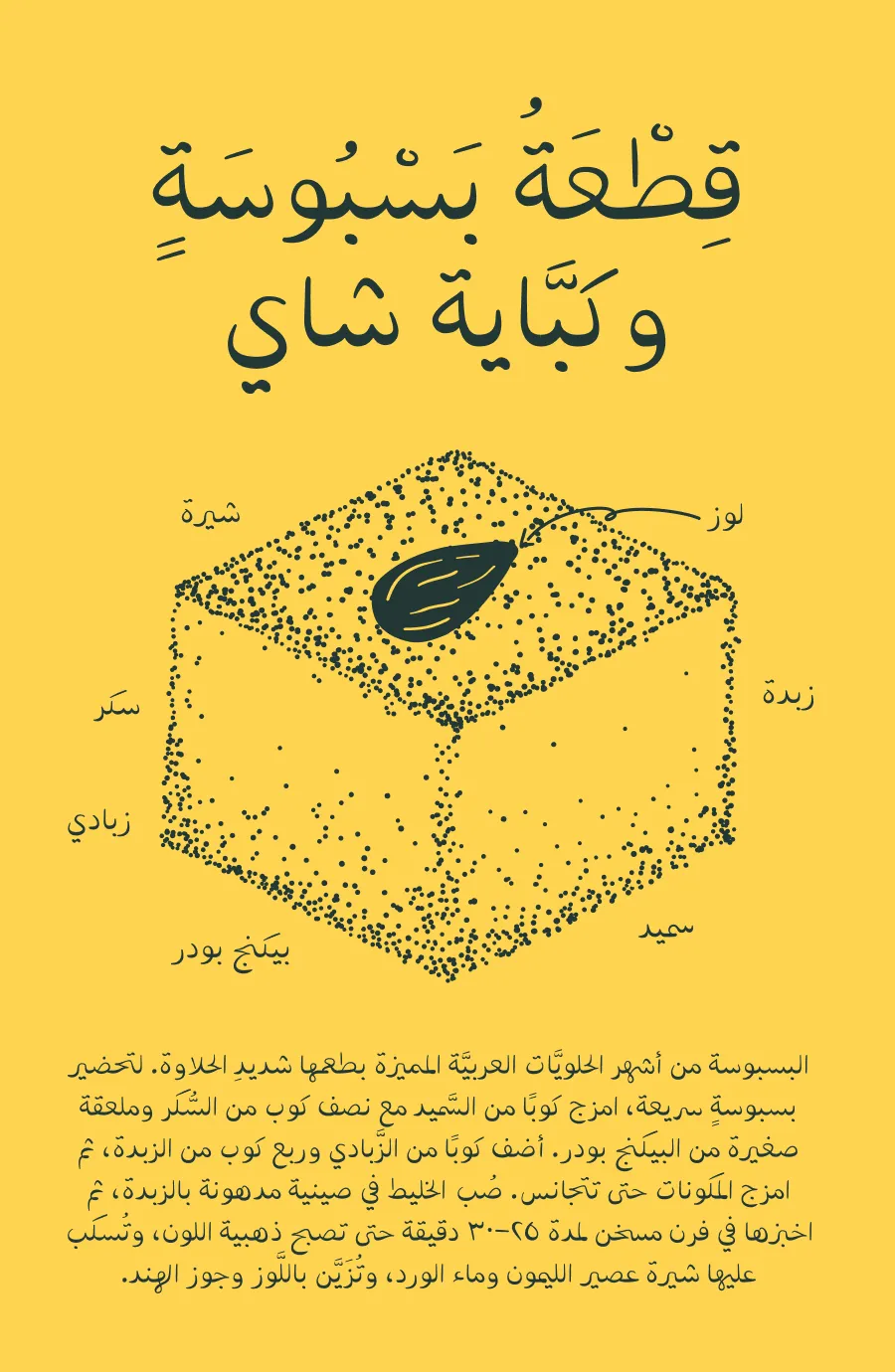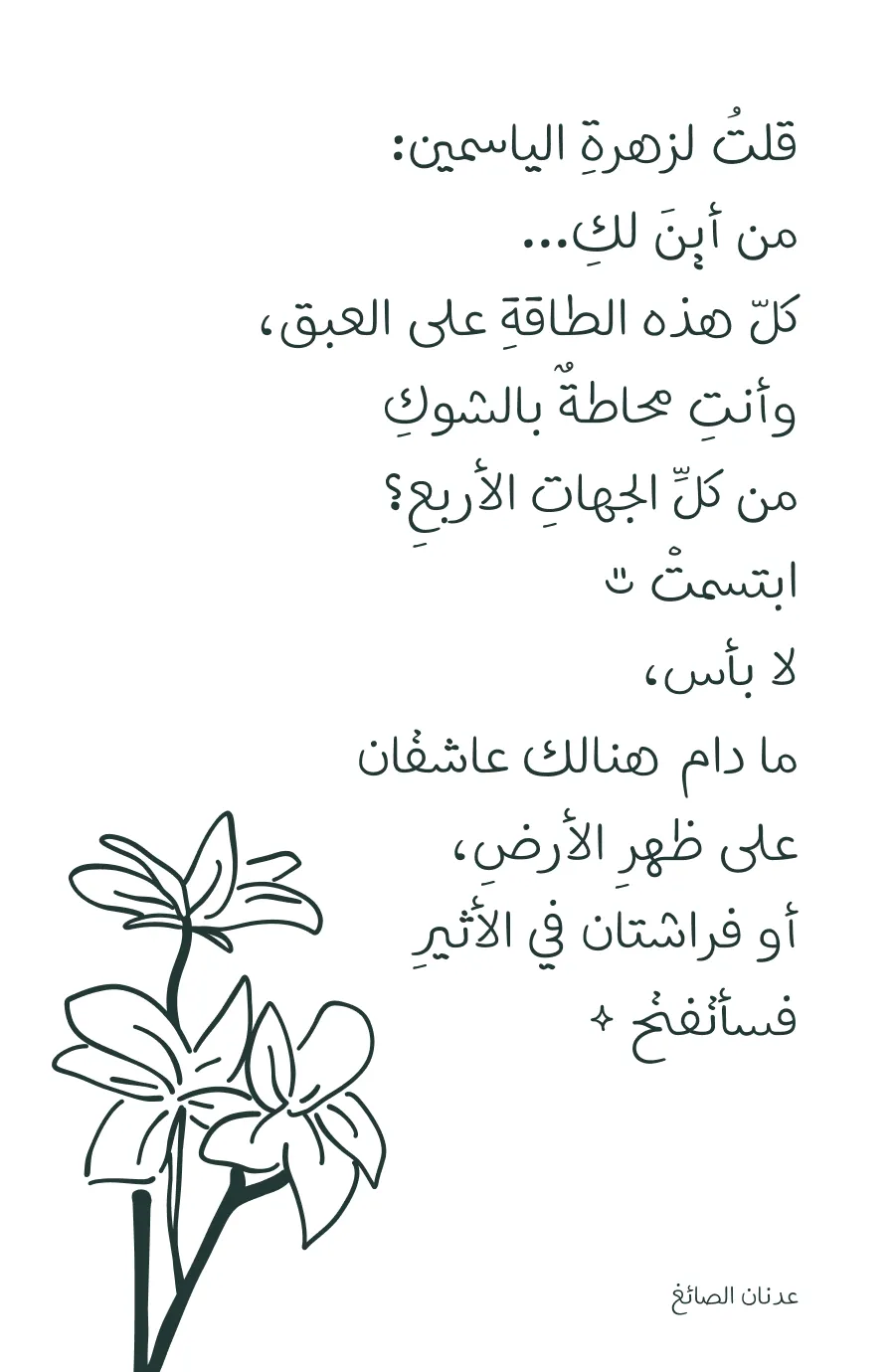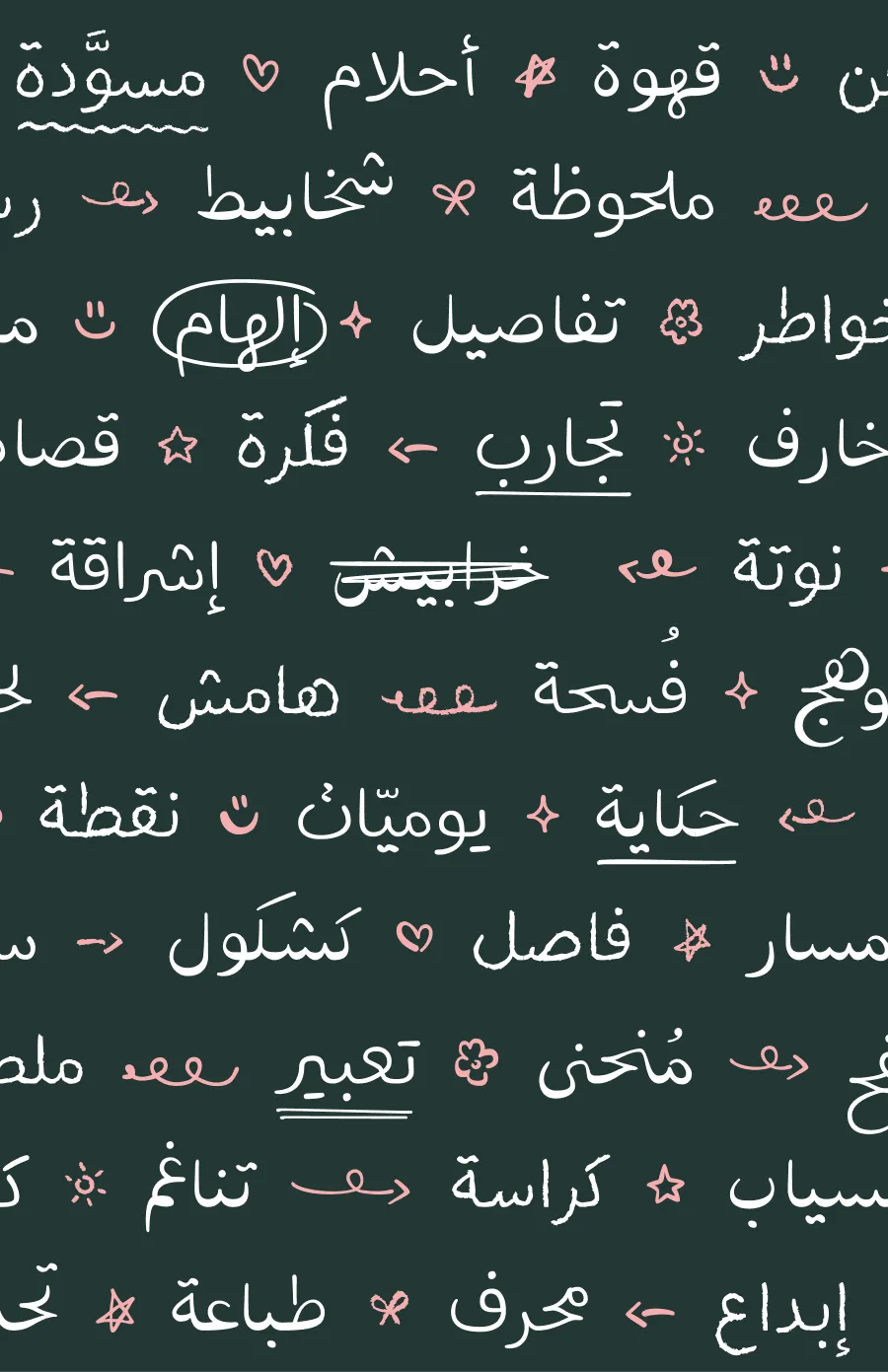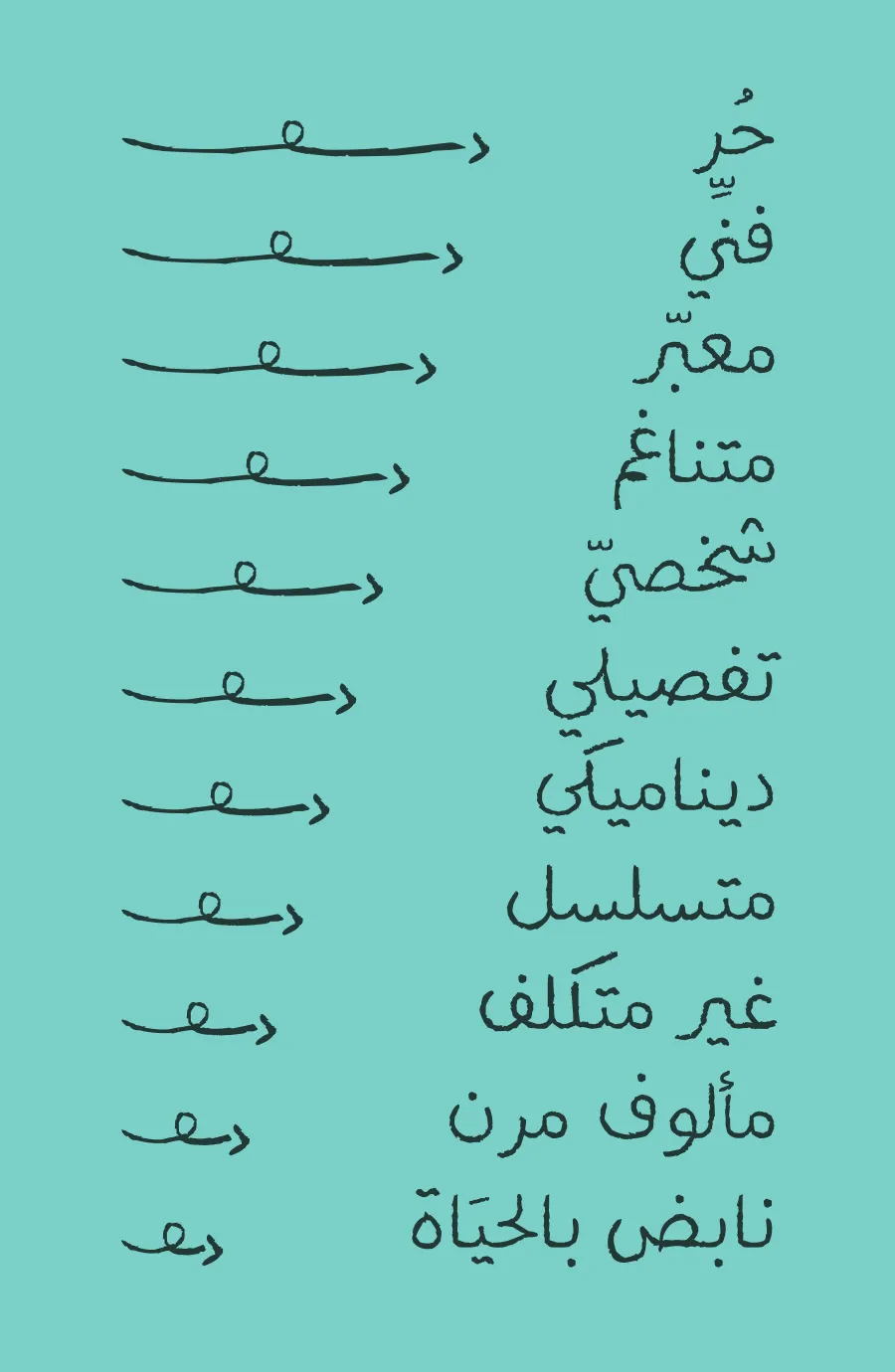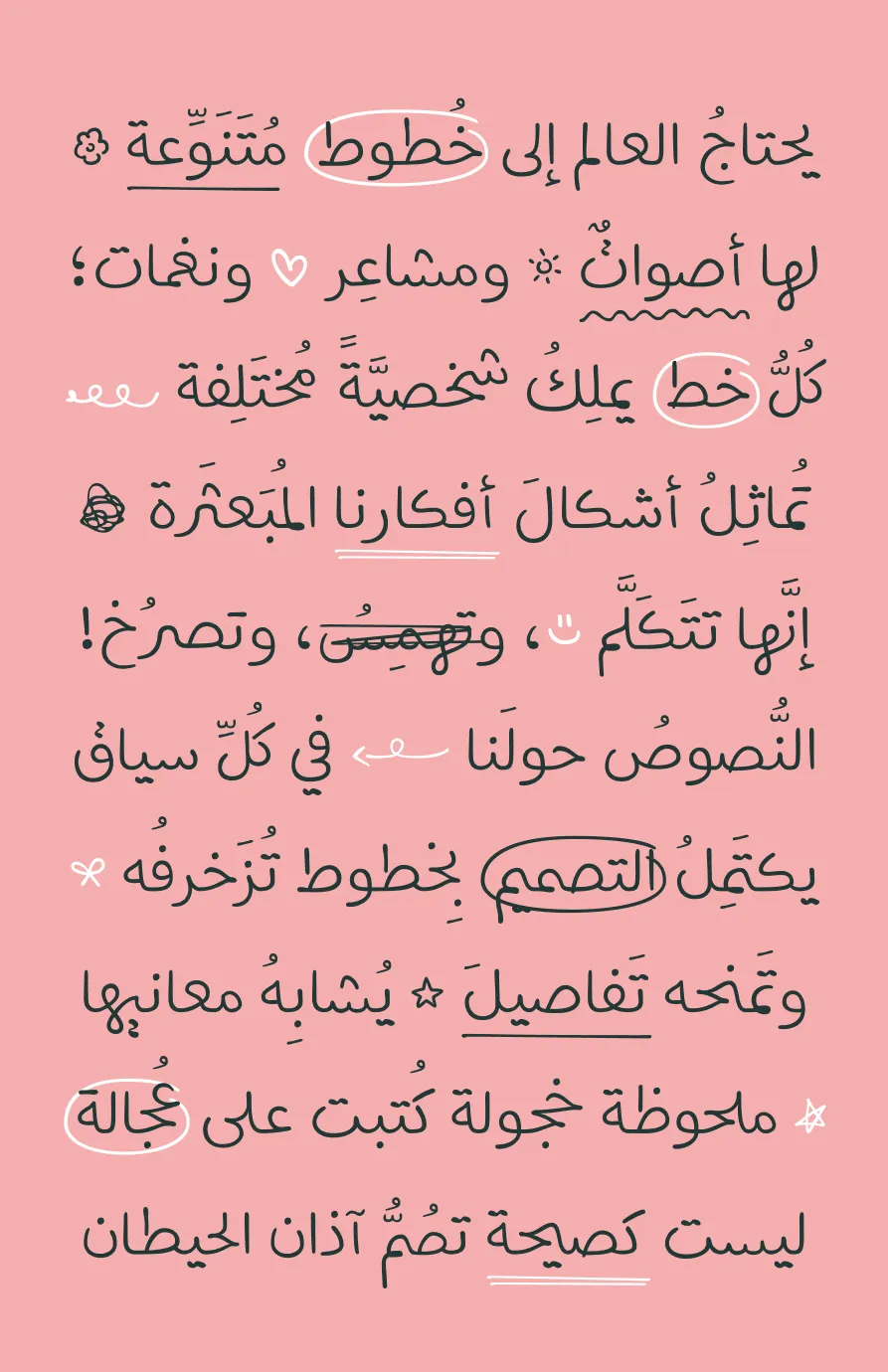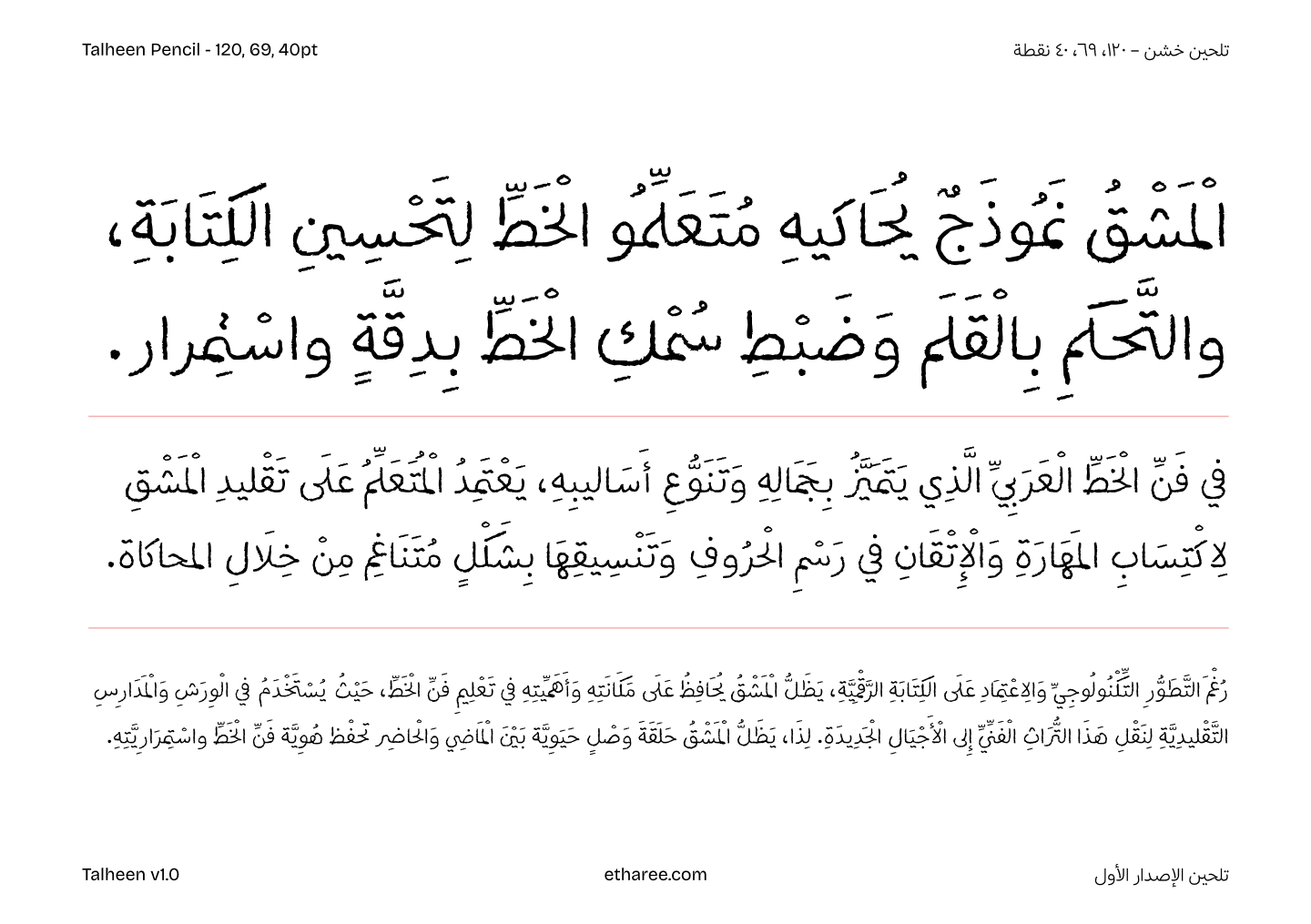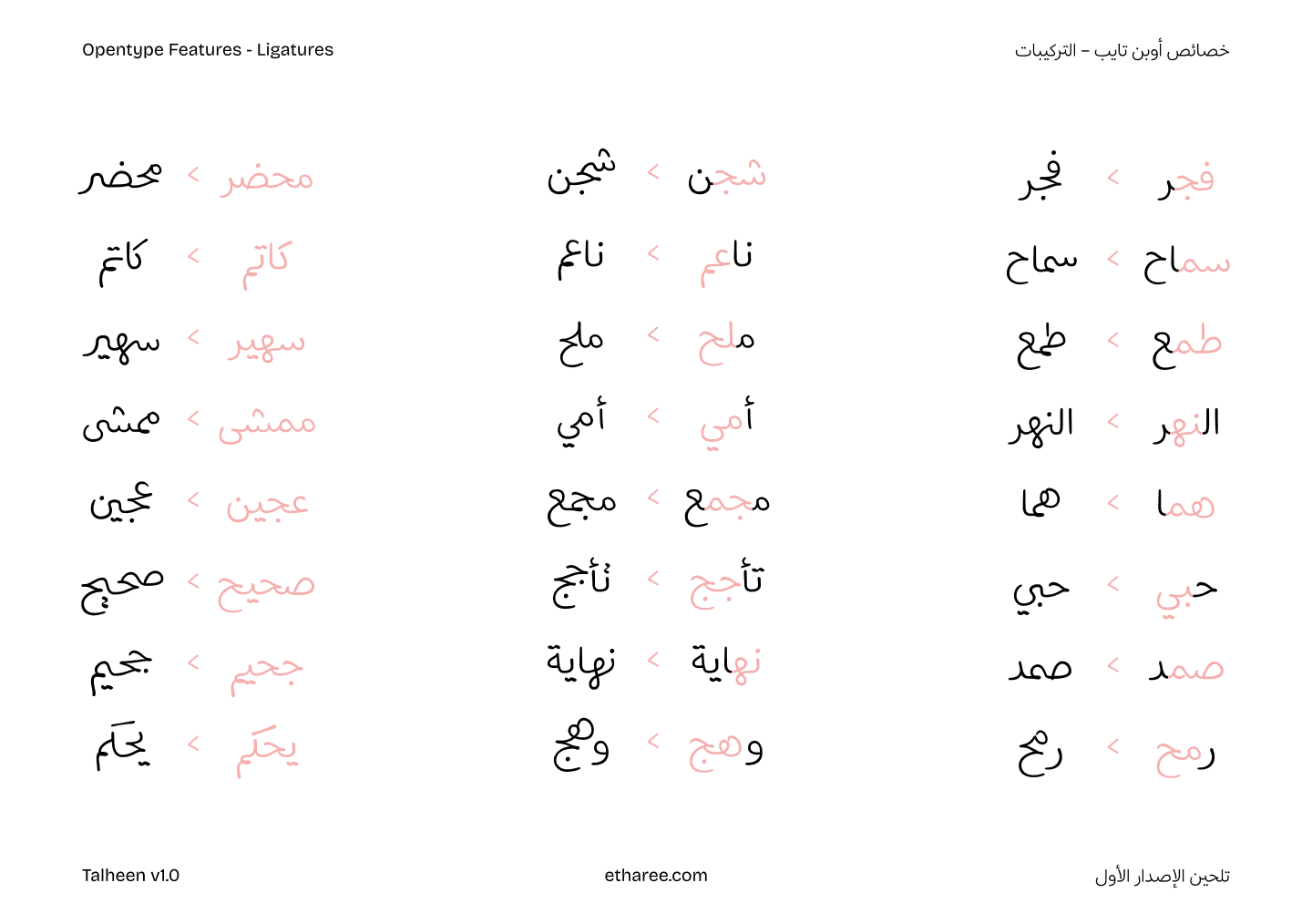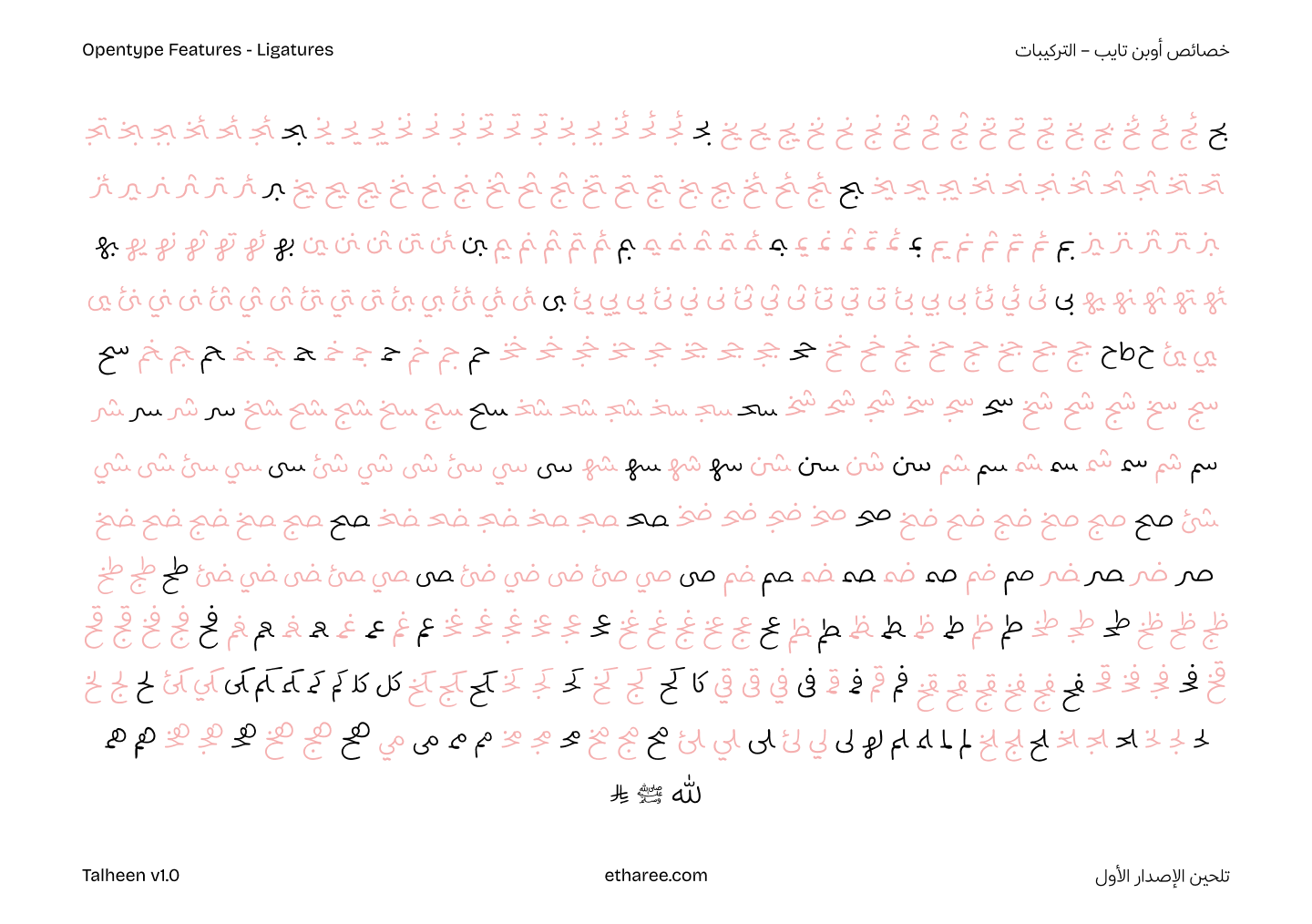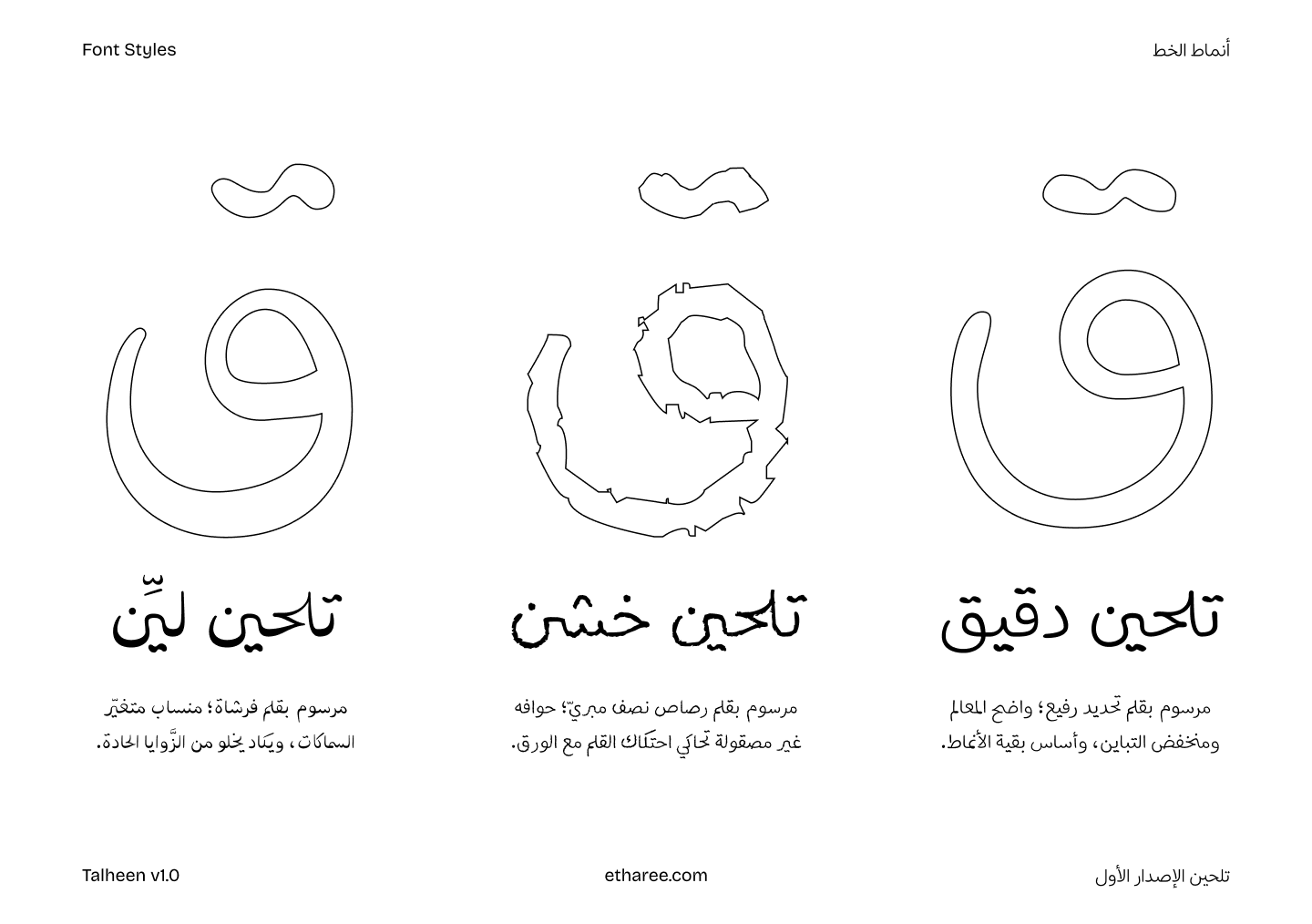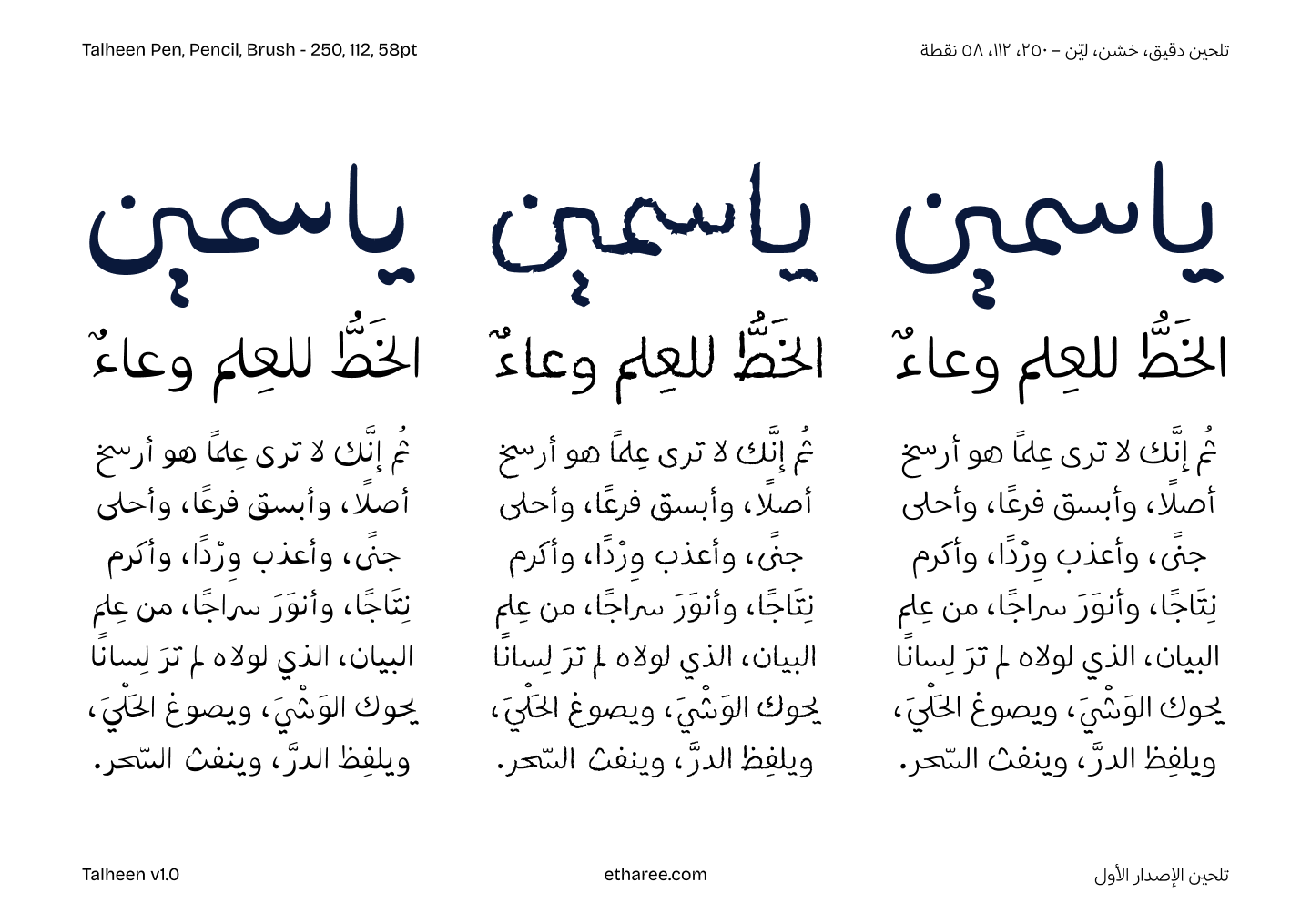
خط تلحين Talheen typeface
خطٌّ به شيءٌ من العفويَّة *زهرة* وأُلفة الكِتابة اليدويَّة ~-~ مِثل خطِّ زميلٍ في الفصل *قلب* أو خربشات== سريعةٍ على هامِش دفترٍ قديم؛ بعيدٌ عن الإتقانِ الميكانيكيِّ###، ويحتفِظُ ببعضٍ من الفَوضى~~~     ## اليدويَّة الجميلة *شمس*
تلحين عائلة خطوط يدويّة بثلاثة أنماط لكلٌّ منها طابع مختلف. يضفي تلحين لطافةً على مشاريع التصميم؛ لعفويّة تفاصيله التي تحتفظ بخصائص رسم اليد. بدأ العمل على تلحين عام ٢٠٢٣، كفكرة لتوثيق خطّ يديّ، واستمرَّ على امتداد ثلاث سنوات من التطوير والمراجعة. يدعم الخطّ في نسخته الحاليَّة العربيَّة الموسَّعة، واللَّاتينية البسيطة، ويتضمَّن تركيبات وتبديلات تمنح النصّ مظهر الكتابة اليدويَّة.